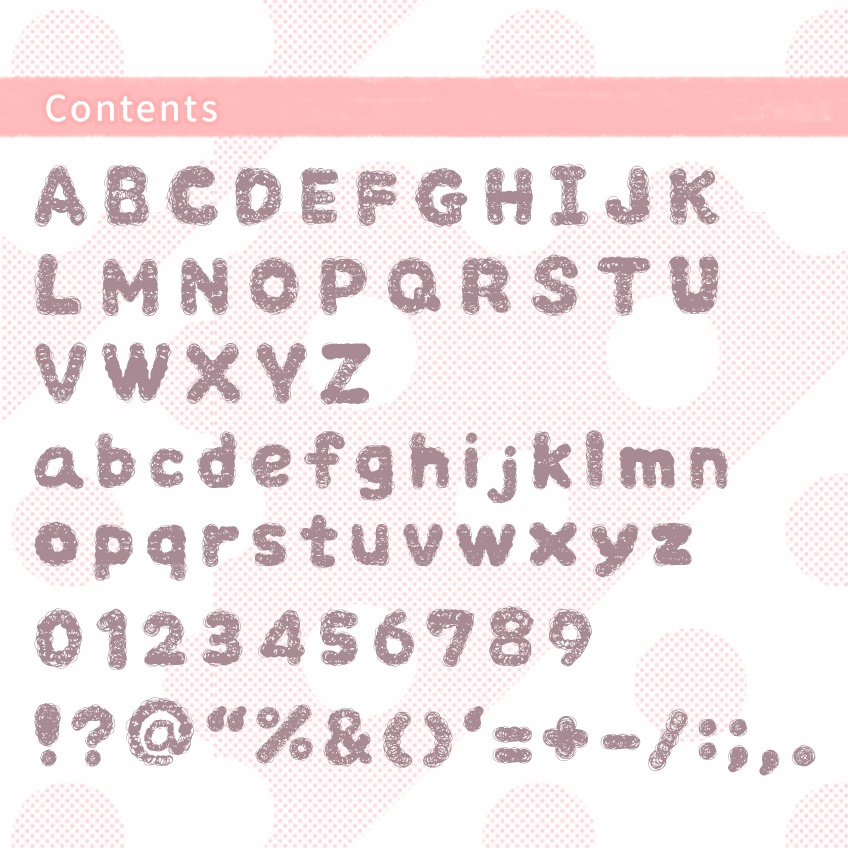
フリーフォント【MOFOOL】もふ~る
「MOFOOLもふ~る」フォントとは 羊毛が文字をまとったような、ほっこりゆるい雰囲気の書体です。 【収録文字】 ・アルファベット大文字/小文字/いくつかの記号 【フォントの形式】 ・OpenType 【ライセンス】 ・個人/商用利用可能。 ・当フォントの著作権はShufuminが所有しています。 ※利用報告・クレジット表記は特に必要ないです。 ・任意で「もふ~るフォント使ったよー」とtwitterなどでつぶやき(お知らせ)くださると、大変うれしいです。 【禁止】 ・当フォントデータの複製、改変、再配布、再販売 ・当フォントを使用した製作物の商標登録、意匠登録 【最後に】 当フォントを使用したことによって発生したいかなる損害につきましては、一切の責任を負いかねます。ご了承ください。